Manuel de Andrade de Figueiredo (1670 - 1735)
No reinado de João V, um
período de significativo avanço das «artes
gráficas» em Portugal, destacou-se Manuel de Andrade de
Figueiredo (16701735), que estabeleceu o que se poderia chamar a
«letra caligráfica portuguesa» na obra:
Nova escola para aprender a ler, escrever, e contar.
Offerecida a Augusta Magestade do senhor Dom João V. Rey de Portugal,
primeira parte por Manoel de Andrade de Figueiredo, Mestre desta Arte nas
Cidades de Lisboa. Occidental, e Oriental.
Na Nova escola há, entre os
exercícios para os alunos, dois poemas visuais assinados por Andrade. O
primeiro deles está escrito no estandarte que um cavaleiro carrega.
É uma quintilha em redondilha maior:
O exercício, e louvor das letras, que o
mundo aclama tem na nobreza o melhor berço, a que ilustra a
fama, por mais sagrado esplendor. |
A Nova Escola, impressa com licenças do
Santo Ofício, do Ordinário e do Paço, também
orienta a forma correta de o mestre repreender seus alunos. O castigo
não se encobre com o amor, pois o mesmo Deus aos que ama castiga. E o
castigo se é demasiado parece tirania, se proporcionado é
remédio, escreve Figueiredo.
A Nova Escola é considerada uma
revolução do ensino no século 18 pela
publicação O pensamento pedagógico em
Portugal, escrita por Rogério Fernandes (Biblioteca Breve).
Andrade de Figueiredo atribuía largo alcance
social à educação. As qualificações dos
súditos, assegurava sem hesitações, provêm da sua
aplicação enquanto meninos e do ensino dos mestres, escreve
o autor. Rogério Fernandes observa, ainda, que Manuel de Andrade de
Figueiredo recusava o método global e preconizava o método
silábico, pois, na formação das sílabas
consistiria o principal e o maior trabalho do menino.
Ao analisar a gramática, Rogério Fernandes
afirma que «o autor atribuía à impreparação
metodológica dos docentes o fato de os discípulos penarem
longamente nas escolas sem aprenderem a ler.»
No entendimento de Rogério Fernandes, Andrade de
Figueiredo tinha uma percepção muito nítida das
necessidades dos professores nas escolas elementares. Ele destaca que
a Nova Escola é, por isso mesmo, a obra pedagógica
portuguesa do século 18 que mais diligencia inserir-se na realidade
escolar, na medida em que pretende constituir um ponto de apoio para o
docente. |
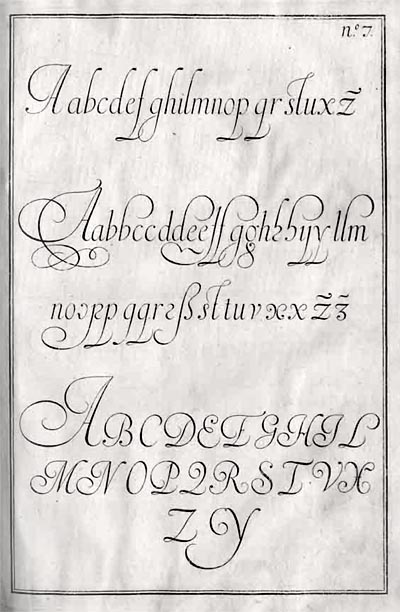
A famosa Nova Escola para Aprender a Ler, Escrever e
Contar foi impressa em 1722. |
Em homenagem a Manuel de Andrade, o typeface designer
português Dino dos Santos
publicou a sua fonte caligráfica Pluma, que integra Pluma Primeyra,
Segunda e Terceyra.
A fonte Methodo, igualmente dotada de três variantes,
é uma reprodução dos exercícios exigidos a
estudantes, patentes no Methodo Calligraphico, de Pinto de Mesquita.
A fonte Andrade, de Dino dos Santos, publicada em 2005.
Edição fac-similada do mais belo e célebre
livro português sobre o ensino da leitura e da escrita bem como da arte
da caligrafia. |